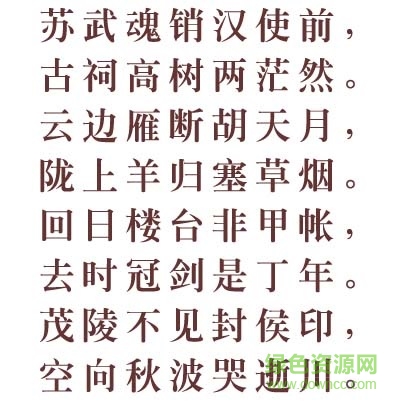
文鼎大標宋簡字體是一款方正端莊的中文簡體字體。該字體在大字報中比較常見,多位醒目的開頭使用。win10系統(tǒng)也可使用,有需要的朋友,趕快來綠色資源網(wǎng)下載吧!
宋體,是為適應(yīng)印刷術(shù)而出現(xiàn)的一種漢字字體。筆畫有粗細變化,而且一般是橫細豎粗,末端有裝飾部分(即「字腳」或「襯線」),點、撇、捺、鉤等筆畫有尖端,屬于襯線字體(serif),常用于書籍、雜志、報紙印刷的正文排版。
宋朝文化興盛,印刷業(yè)有了巨大發(fā)展,從南宋時期,在臨安等地的印刷作坊里就開始出現(xiàn)了類似印刷體的字體,后世稱之為仿宋體。明朝時期,文人追捧宋刻本書籍,于是刻匠們加粗仿宋體的豎線和筆畫的端點以抵抗刻版磨損,卻依舊稱之“宋體”?,F(xiàn)代的所謂宋體基本上就是這樣成型的。